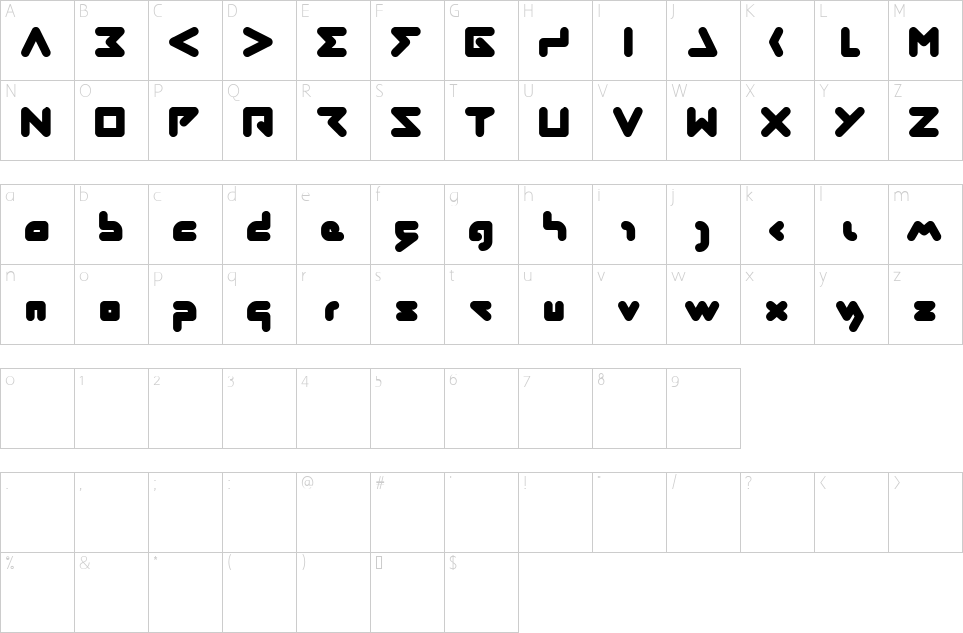
A Abstrasctik Font oferece um estilo minimalista e moderno para designers e criativos de todo o mundo. Feita por um designer não identificado, essa fonte está disponível tanto para usuários de Windows quanto para Mac. Com um design leve e contemporâneo, a Abstrasctik pode ser a escolha perfeita para qualquer projeto que exija uma aparência minimalista e elegante. Com mais de 6 mil downloads, é evidente que designers de todos os níveis estão utilizando e se apaixonando por esta fonte. Se você está procurando uma fonte versátil para seus projetos, a Abstrasctik é uma excelente opção para adicionar ao seu conjunto de ferramentas digitais.